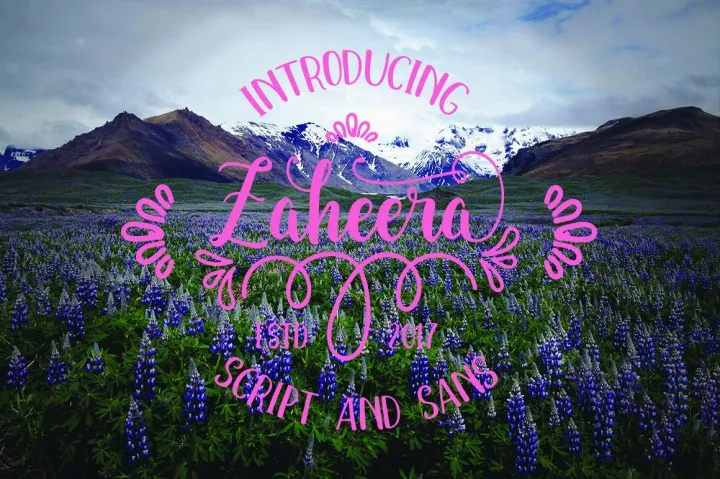
Zaheera Script Font – Download Grátis
A Zaheera Script Font é uma seleção elegante para qualquer projeto visual que valorize a delicadeza e a modernidade. Criada por dayatz2009 usando uma caneta torta, essa fonte possui um estilo script perfeito para designs femininos, bem como para criações mais contemporâneas. A Zaheera é confortável tanto para designers quanto fotógrafos, especialmente para projetos que incluem wedding invitations, roupas personalizadas e identidades de marca. Além disso, sua simplicidade também a torna uma escolha ideal para trabalhos em têxteis, proporcionando um acabamento único a qualquer projeto. Com uma grande variedade de aplicações, essa fonte é certamente uma adição valiosa à coleção de qualquer designer gráfico apaixonado por detalhes e estilo.